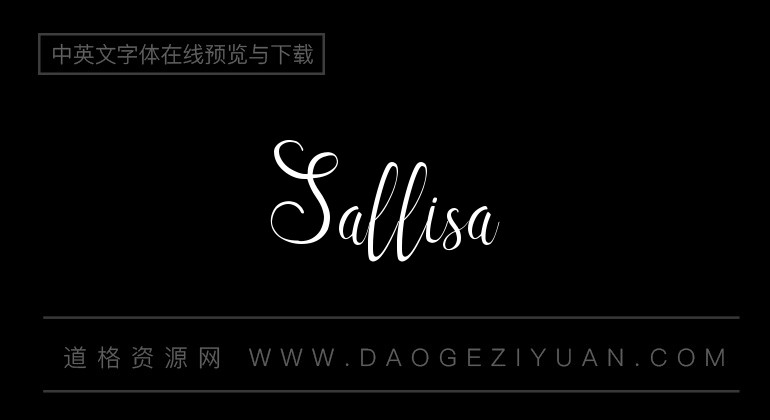
Sallisa
? Sallisa字体是一款由Sudtipos设计的多功能字体,它具有清晰的视觉效果,可以满足各种设计需求。Sallisa字体拥有一系列的细节,包括双重锯齿,圆润的线条,折曲的角度,以及精细的线条等,可以为设计师提供丰富的选择。它的设计风格适用于多种应用,如印刷,网页,品牌标识等,可以为设计师提供丰富的设计资源。
Sallisa是一款非常不错的手写艺术字体,具有很好的视觉感,适合于文化类的宣传设计、商业类品牌的广告和产品包装设计以及个性化文字排版等较多场景。